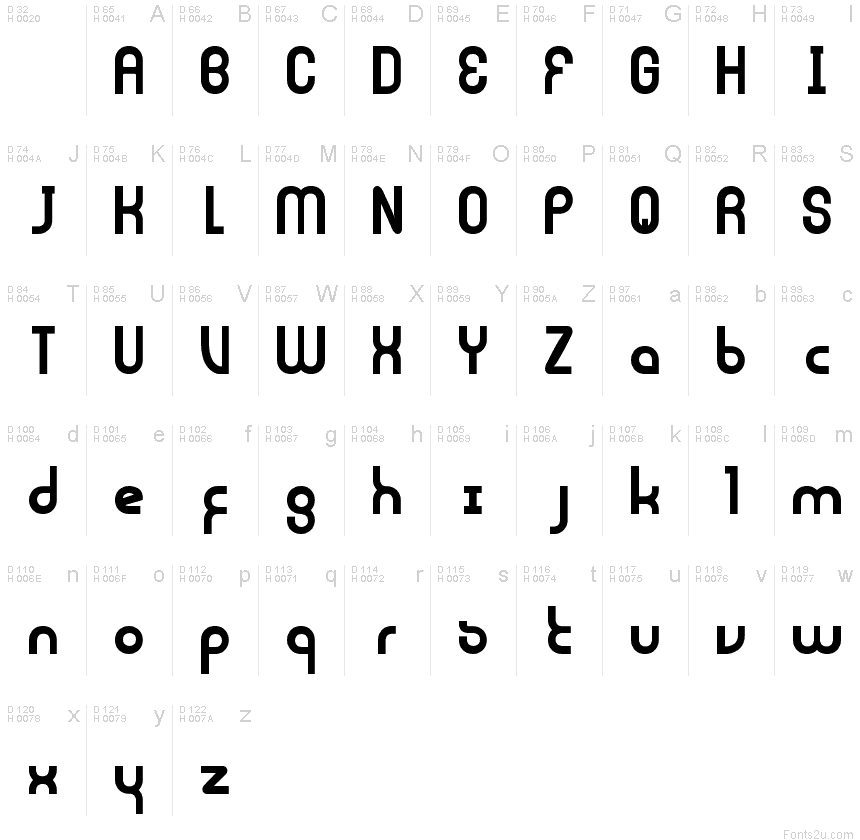
Joulu Fontti od Fenotype to darmowy, zaokrąglony, geometryczny krój typu display o szerokich pociągnięciach i prostych formach. Jego okrągłe łuki i tępe zakończenia sprawiają, że litery wydają się miękkie, ale solidne. Formy są czyste i zwarte.
Opakowania zabawek to jego najmocniejsze zastosowanie, w którym przyjazna grubość może zmienić nazwę produktu w łatwo rozpoznawalną etykietę. Sprawdza się również na plakatach dla dzieci oraz w luźnych grafikach eventowych, zwłaszcza gdy ilustracje wykorzystują te same koła, zaokrąglone bloki i uproszczone sylwetki co litery.